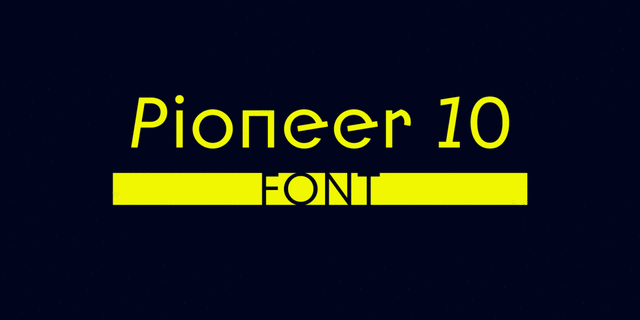
Pioneer 10 – экспериментальный шрифт без засечек, сочетающий геометрические элементы прямого и наклонного шрифта. Идея его создания возникла в результате работы школы Баухаус и конструктивистов начала ХХ века. Поддерживает расширенную латиницу, кириллицу и функции OpenType. Шрифт разработан в 2019 году. Шрифтовой дизайнер Игорь Косинский.
Ассоциации c семейством Pioneer 10Качества и характер:
ломаный, твердый, оригинальный, игривый, квадратный, урбанистический, экспериментальный, звонкий, яркий, активный, заметный, смелый, мотивирующий, угловатый, острый, рубленый, элементарный, резкий, четкий, тусовочный, динамичный, сумасшедший, странный, урбанистичный, городской, клубный, характерный, забавный, необычный, прикольный, молодежный, инопланетный, свежий, модный, интересный, смешной, современный, стальной, ровный, холодный, машинный, стеклянный, ледяной
— Особенности семейства Pioneer 10Хит десятилетия: